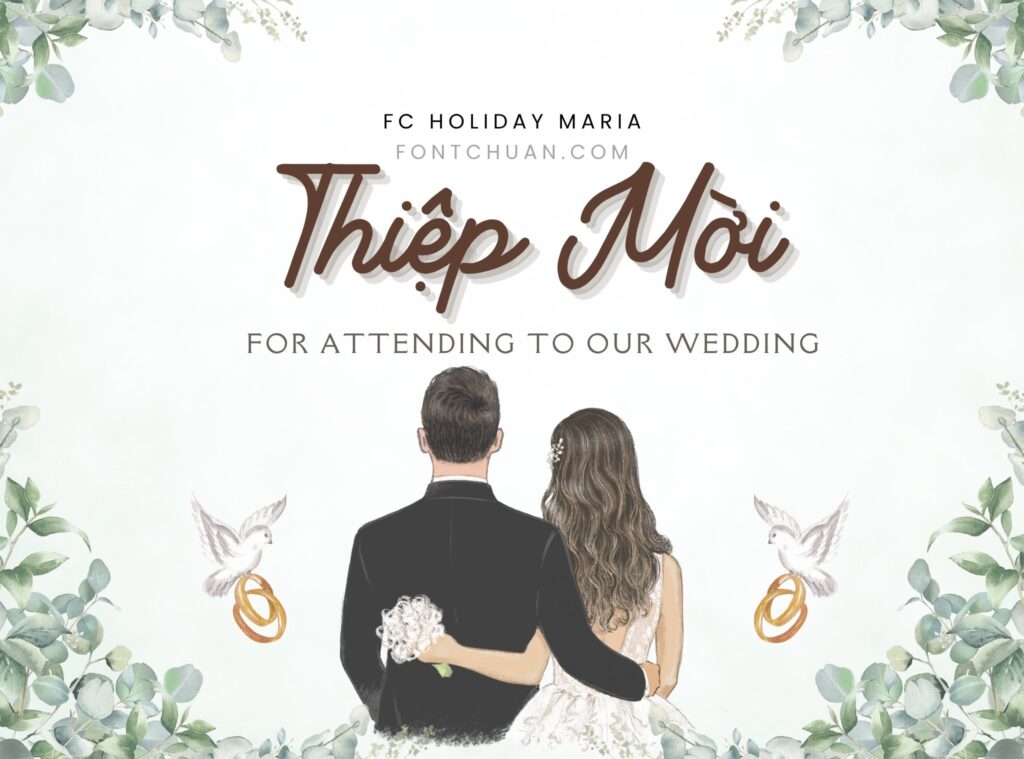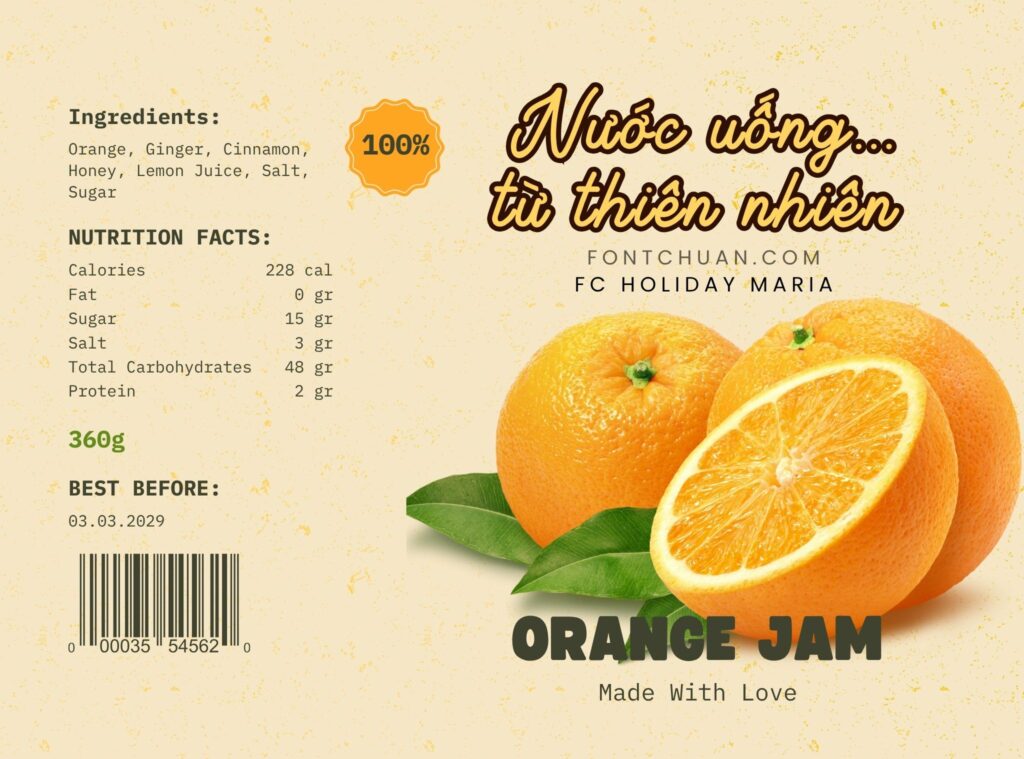
Font FC Holiday Maria Regular Việt Hóa
Font Holiday Maria là một kiểu chữ script đơn tuyến ngọt ngào và vui tươi, được thiết kế bởi Salamahtype. Với các đường nét mềm mại và tinh tế, Holiday Maria mang lại cảm giác ấm áp và thân thiện, phù hợp cho các dự án thiết kế như thiệp mời, logo, tiêu đề và các ấn phẩm truyền thông khác. Đây cũng là lựa chọn hoàn hảo để sáng tạo thành font chữ Trung Thu, giúp thiết kế poster, bao bì bánh, hay thiệp chúc mừng mùa lễ hội trở nên gần gũi và ý nghĩa hơn.
Khác với phiên bản Font việt hoá Holiday Maria Regular khác, Font FC Holiday Maria Regular do Font Chuẩn thực hiện việc hóa lại từ đầu và phân phối miễn phí, phiên bản Font này hỗ trợ đa ngôn ngữ, bao gồm tiếng Việt, giúp người dùng dễ dàng áp dụng trong các dự án sáng tạo của mình.
Ứng dụng làm thiệp mời Font FC Holiday Maria Regular Việt Hóa
Về đặc điểm thiết kế, Holiday Maria sở hữu các ký tự với nét chữ mượt mà và liền mạch, tạo nên sự thu hút và ấn tượng cho người xem. Font này phù hợp cho nhiều ứng dụng như thiết kế thương hiệu, bao bì sản phẩm và các ấn phẩm truyền thông khác. Các ngành nghề như quảng cáo, thiệp cưới, ẩm thực, bao bì sản phẩm… có thể tận dụng Holiday Maria để tạo ra những sản phẩm ấn tượng và chuyên nghiệp.